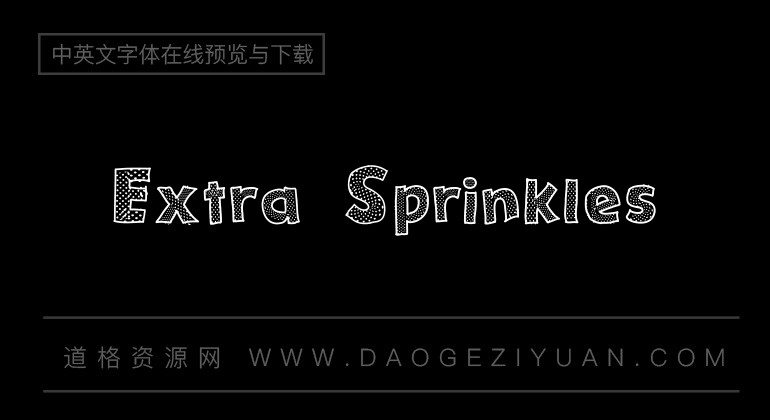
Extra Sprinkles
Extra Sprinkles是一款精致的花式字体,它具有多种类型的字体,比如斜体、粗体、细体等,它的外观极具视觉冲击力,可以为任何网页、印刷品或其他设计项目提供引人注目的外观。它的字体非常细腻,使用者可以根据自己的需求调整字体大小,以便更好地表达自己的想法。它的字体也具有良好的可读性,使用者可以清晰地阅读文本。
Extra Sprinkles是一款非常不错的手写艺术字体,具有很好的视觉感,适合于文化类的宣传设计、商业类品牌的广告和产品包装设计以及个性化文字排版等较多场景。
Extra Sprinkles字符映射图